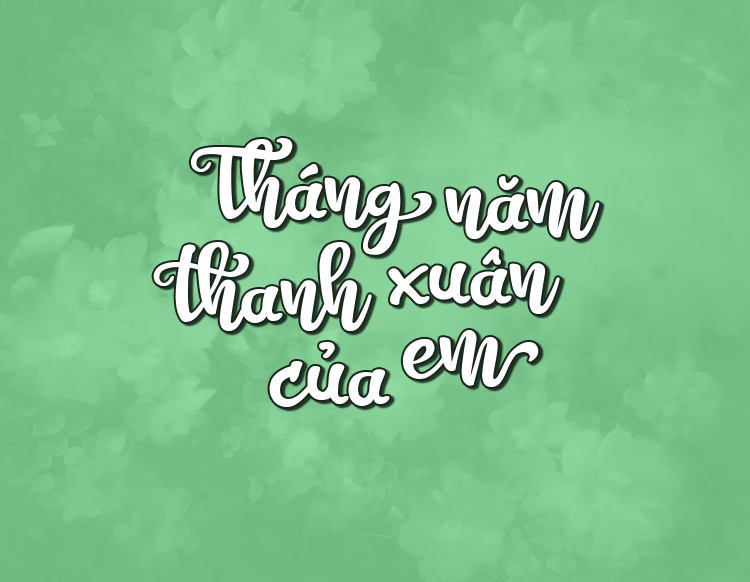
Giới thiệu về Font việt hoá MJ Meytanio
Trong thế giới thiết kế đồ họa hiện đại, việc lựa chọn một Font Chữ phù hợp đóng vai trò quan trọng trong việc truyền tải thông điệp. Font việt hoá MJ Meytanio là một lựa chọn tuyệt vời cho những ai đang tìm kiếm sự kết hợp hoàn hảo giữa nét cổ điển và hơi thở hiện đại. Bộ font này không chỉ mang lại vẻ đẹp sang trọng mà còn đảm bảo tính thẩm mỹ cao cho mọi tác phẩm nghệ thuật. Nhờ quá trình việt hóa tỉ mỉ, người dùng tại Việt Nam có thể dễ dàng sử dụng bộ gõ tiếng Việt mà không lo lỗi hiển thị dấu.
Ưu điểm nổi bật của Font việt hoá MJ Meytanio
Thiết kế tinh tế và chuyên nghiệp
Font việt hoá MJ Meytanio sở hữu các đường nét uyển chuyển, thanh thoát nhưng vẫn giữ được sự chắc chắn cần thiết. Điều này giúp bộ font trở nên đa năng, phù hợp cho cả thiết kế bìa sách, thiệp mời đám cưới hay các dự án nhận diện thương hiệu cao cấp. Các ký tự được chăm chút kỹ lưỡng, tạo nên sự cân đối thị giác tuyệt vời trên cả bản in và hiển thị số.
Khả năng ứng dụng linh hoạt
Không chỉ dừng lại ở các thiết kế sang trọng, Font việt hoá MJ Meytanio còn rất được ưa chuộng trong việc làm tiêu đề video, thiết kế banner quảng cáo hoặc trình bày văn bản sáng tạo. Khả năng tương thích tốt với các phần mềm thiết kế phổ biến như Adobe Photoshop, Illustrator giúp các nhà thiết kế tối ưu hóa quy trình làm việc hiệu quả nhất.
Để tận dụng tối đa vẻ đẹp của Font việt hoá MJ Meytanio, bạn nên kết hợp nó với các tông màu trung tính hoặc các phông chữ không chân (sans-serif) đơn giản để tạo sự tương phản. Khi cài đặt, hãy đảm bảo hệ thống máy tính của bạn đã được cập nhật để hiển thị tốt nhất các ký tự đặc biệt. Đây thực sự là một lựa chọn không thể bỏ qua cho kho tài nguyên của bất kỳ designer nào. Hãy trải nghiệm ngay Font Miễn Phí, Font Việt Hóa, Font việt hoá MJ Meytanio để nâng tầm các dự án sáng tạo của bạn một cách nhanh chóng và chuyên nghiệp nhất ngay từ hôm nay.